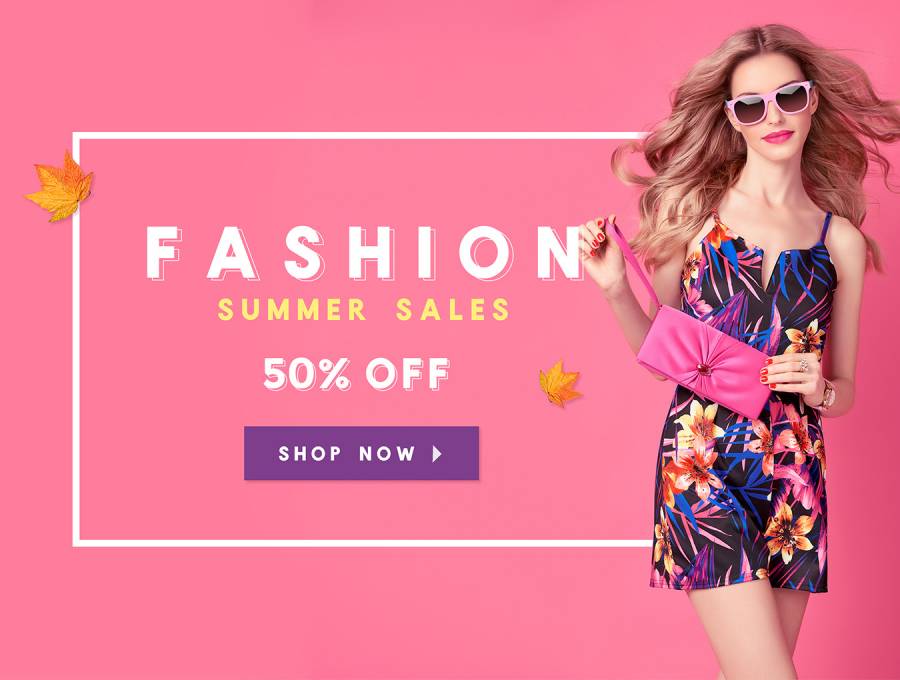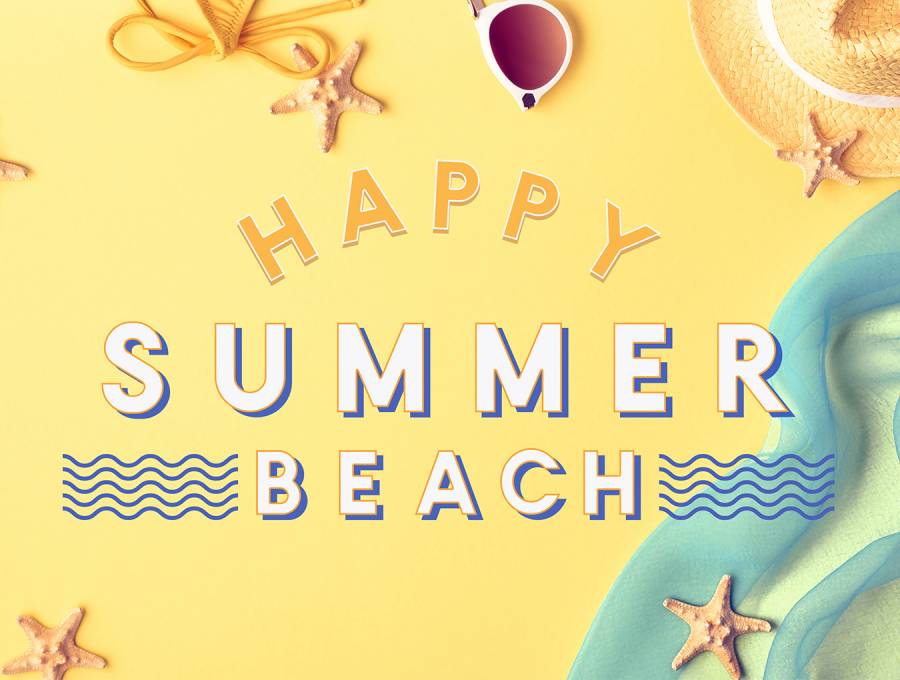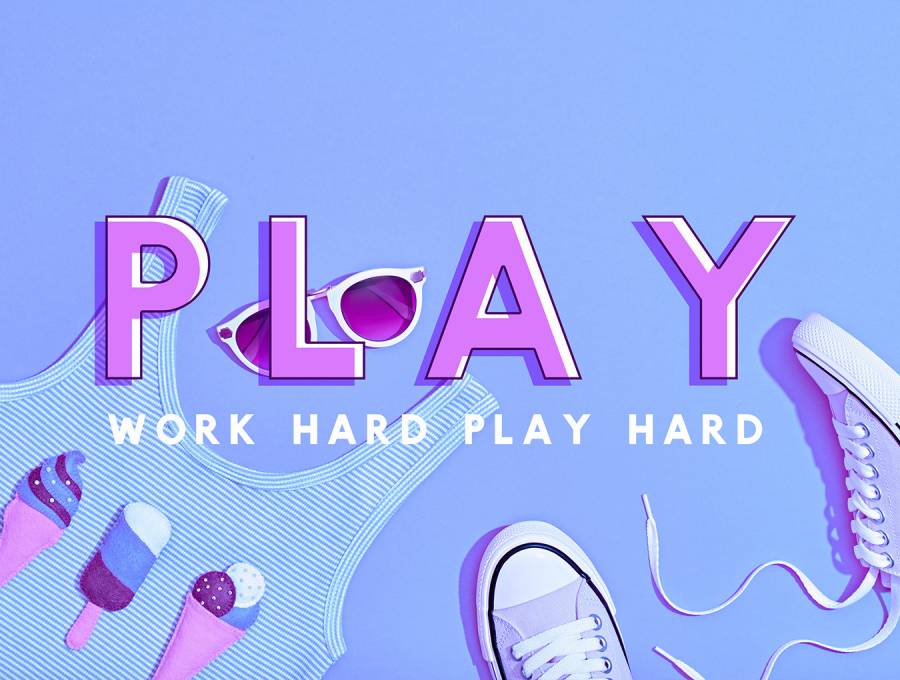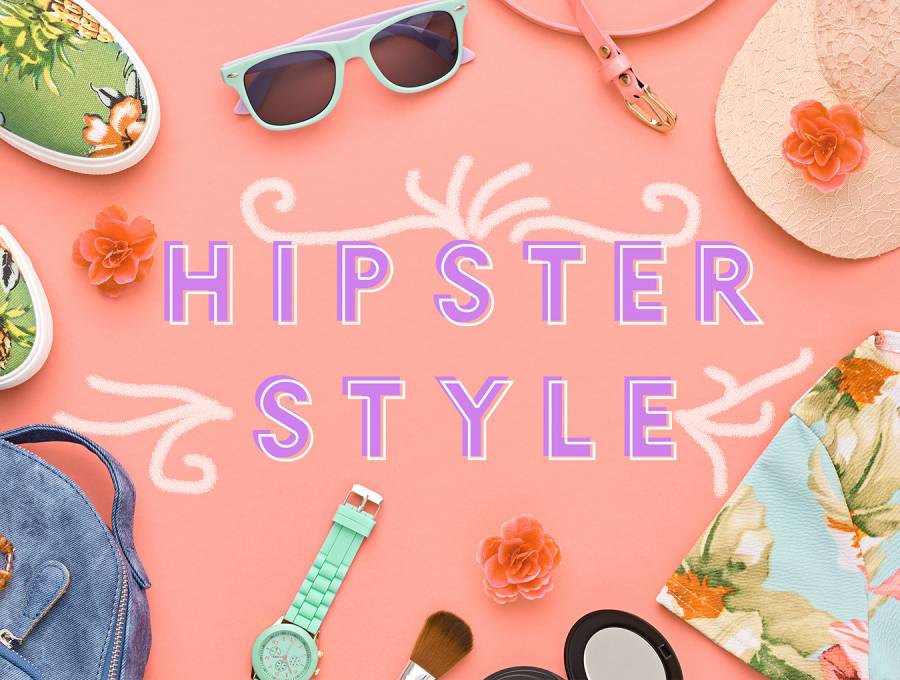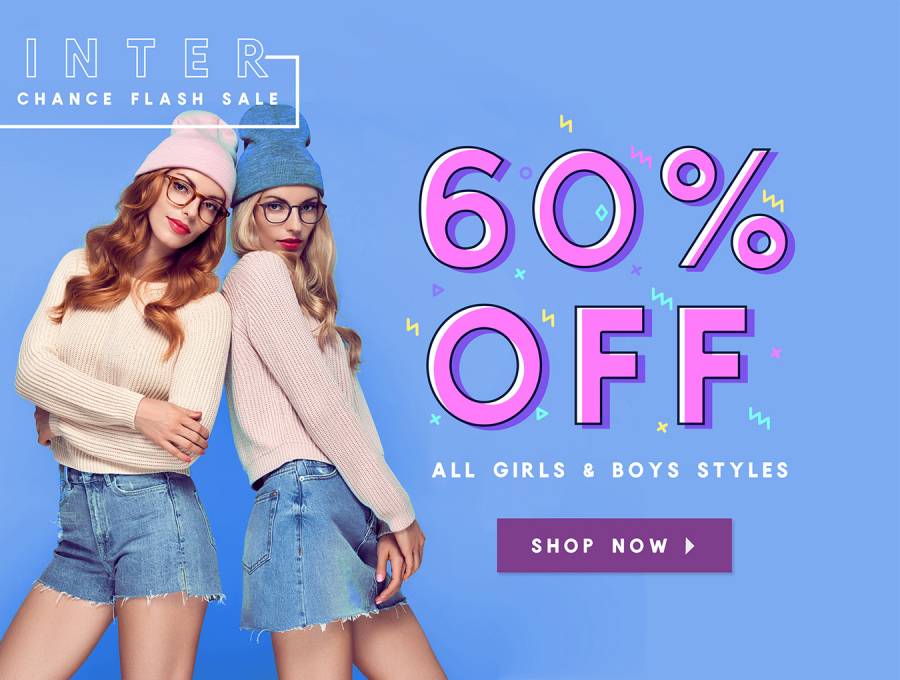
Victoria Sans Serif优雅标题类型字体,Victoria Sans Serif字体
维多利亚Sans是简单干净的魅力和大胆的字体,非常适合用于标题,横幅,徽标,海报等等。它是一个可爱而独特的无衬线字体,让您可以让每个单词看起来都很时尚!它最适合现代/干净的设计,标识,标题,横幅和模板等。如果你想尝试一个优雅的外观,它看起来华丽的所有大写间距,或美丽的大写和小写字母为完全永恒的东西。
字体有四种不同的风格:粗体,粗体轮廓,粗体斜体,粗体斜体轮廓和多语言支持。